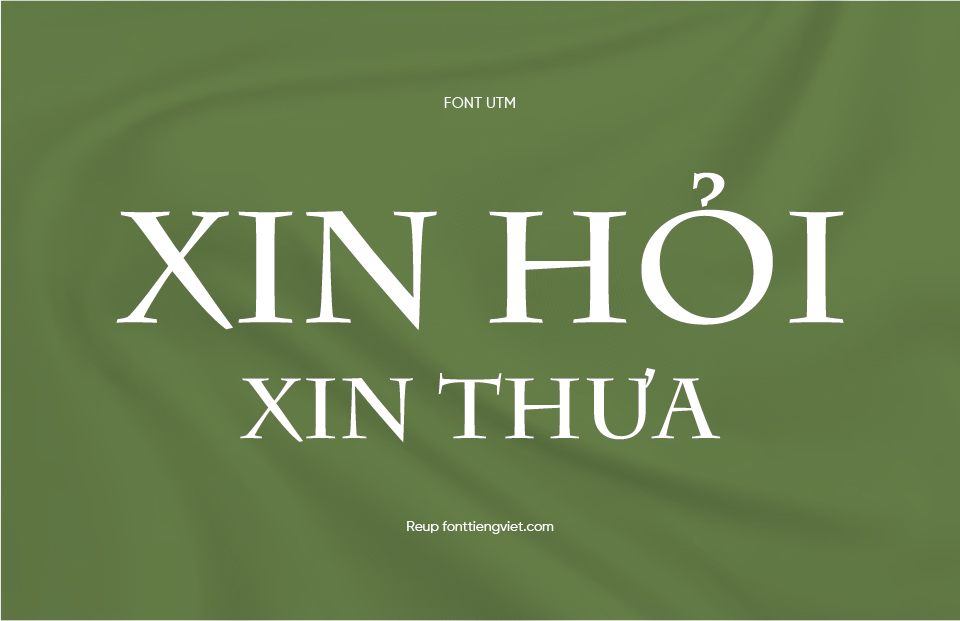
Font Việt hóa UTM Charlemagne
Font Việt hóa UTM Charlemagne – Sự lựa chọn đẳng cấp cho thiết kế cổ điển
Giới thiệu về Font Việt hóa UTM Charlemagne
Trong thế giới thiết kế đồ họa, việc lựa chọn một Font Miễn Phí phù hợp đóng vai trò quyết định đến linh hồn của tác phẩm. Font Việt hóa UTM Charlemagne là một bộ chữ mang phong cách hoàng gia, lấy cảm hứng từ những ký tự khắc trên đá thời Trung cổ. Với các đường nét thanh mảnh nhưng vô cùng dứt khoát, bộ font này mang lại cảm giác sang trọng, uy nghi và đậm chất lịch sử. Đây là lựa chọn hàng đầu cho các dự án yêu cầu tính thẩm mỹ cao và sự trang trọng tuyệt đối.
Đặc điểm nổi bật của bộ chữ UTM Charlemagne
Thiết kế mang hơi thở lịch sử
Font Việt hóa UTM Charlemagne không chỉ đơn thuần là các ký tự, mà còn là sự tái hiện của nghệ thuật Typography cổ điển. Các chữ cái được thiết kế với chân nhọn (serif) đặc trưng, tạo nên sự cân đối và dễ nhìn trên nhiều bề mặt khác nhau. Điều này giúp các bạn học sinh và giáo viên dễ dàng ứng dụng vào việc làm bìa báo tường, thiết kế thiệp mời hay các tài liệu học tập mang phong cách trang trọng.
Khả năng ứng dụng linh hoạt
Dù mang diện mạo cổ xưa, bộ font này vẫn hoạt động cực tốt trong các thiết kế hiện đại như menu nhà hàng, bao bì sản phẩm cao cấp hoặc tiêu đề phim. Nhờ được Việt hóa hoàn chỉnh bởi đội ngũ UTM, người dùng có thể gõ tiếng Việt có dấu một cách mượt mà, không lo bị lỗi font hay mất ký tự khi trình bày văn bản.